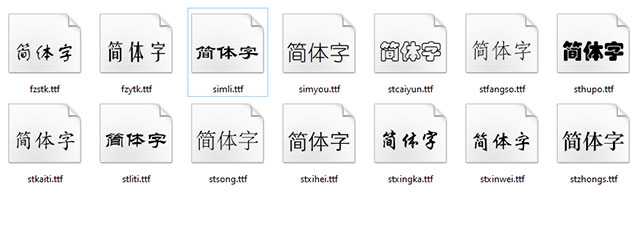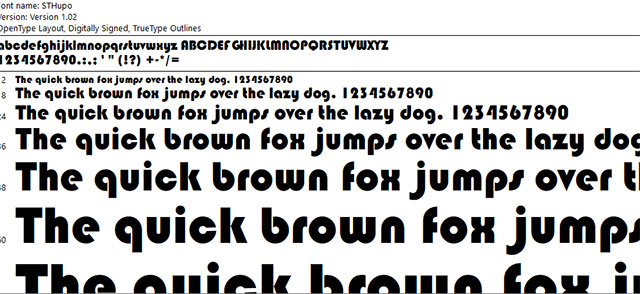
Việc tiếp cận và sử dụng ngôn ngữ Trung Quốc ngày càng trở nên phổ biến trong thời đại toàn cầu hóa. Cho dù bạn là sinh viên, nhà nghiên cứu, doanh nhân hay đơn giản chỉ là người yêu thích văn hóa Trung Hoa, khả năng đọc, viết và hiển thị tiếng Trung trên máy tính là điều vô cùng cần thiết. Để thực hiện điều này, việc sở hữu một bộ font chữ tiếng Trung Quốc chất lượng cao là bước đầu tiên và quan trọng nhất. Bài viết này sẽ hướng dẫn bạn tìm hiểu về bộ font chữ tiếng Trung Quốc, cách tải về và sử dụng hiệu quả.
Tổng quan về bộ font chữ tiếng Trung Quốc
Mỗi font chữ trong bộ này đều được thiết kế tỉ mỉ, thể hiện sự tinh tế trong từng nét chữ. Điều này giúp khắc phục những khó khăn trong việc đọc và viết tiếng Trung trên máy tính, đặc biệt là đối với những người mới bắt đầu làm quen với ngôn ngữ này. Sự đa dạng về kiểu chữ cũng giúp cho việc tạo ra các ấn phẩm, tài liệu liên quan đến tiếng Trung trở nên sinh động và hấp dẫn hơn.
Bộ font chữ bao gồm các font chữ phổ biến và được sử dụng rộng rãi, bao gồm: FZShuti, FZYaoti, LiSu, YouYuan, STCaiYun, STFangSong, STHupo, STKaiti, STLiti, STSong, STXihei, STXingkai, STXinwei, STZhongsong và Simsun. Mỗi font chữ có dung lượng khác nhau, dao động từ 3.09 MB đến 12.1 MB, phản ánh sự khác biệt về thiết kế và độ phức tạp. Sự đa dạng này giúp người dùng có nhiều sự lựa chọn để phù hợp với từng loại tài liệu, ấn phẩm hoặc mục đích sử dụng khác nhau. Ví dụ:
- Font chữ trang trọng: STFangSong, STZhongsong thích hợp cho các tài liệu chính thức, ấn phẩm quan trọng.
- Font chữ hiện đại: STKaiti, STXihei phù hợp với các bài viết trên mạng xã hội, tin nhắn, email.
- Font chữ nghệ thuật: FZShuti, FZYaoti, STXingkai mang đến vẻ đẹp truyền thống, thích hợp cho các tác phẩm nghệ thuật, thiệp chúc mừng.
Việc cung cấp nhiều font chữ khác nhau giúp người dùng không bị bó buộc trong một kiểu chữ duy nhất, tạo điều kiện để họ thể hiện cá tính và sự sáng tạo trong việc sử dụng ngôn ngữ Trung Quốc.
Lợi ích khi sử dụng bộ font chữ tiếng Trung Quốc
Việc sử dụng bộ font chữ tiếng Trung Quốc này mang lại nhiều lợi ích thiết thực:
- Hiển thị chính xác: Bộ font chữ đảm bảo hiển thị chính xác các ký tự tiếng Trung, tránh tình trạng bị lỗi font, ký tự bị lỗi hoặc không hiển thị. Điều này đặc biệt quan trọng khi bạn cần đọc, viết hoặc chỉnh sửa tài liệu tiếng Trung.
- Tăng tính thẩm mỹ: Sự đa dạng về kiểu font chữ cho phép người dùng lựa chọn font chữ phù hợp với từng ngữ cảnh, giúp tăng tính thẩm mỹ cho các tài liệu, ấn phẩm.
- Thỏa sức sáng tạo: Với nhiều font chữ khác nhau, người dùng có thể thỏa sức sáng tạo trong thiết kế đồ họa, tạo ra các sản phẩm ấn tượng và độc đáo.
Tóm lại, việc sử dụng bộ font chữ này giúp người dùng dễ dàng hơn trong việc làm việc với tiếng Trung trên máy tính, nâng cao hiệu quả công việc và học tập.
Kết luận